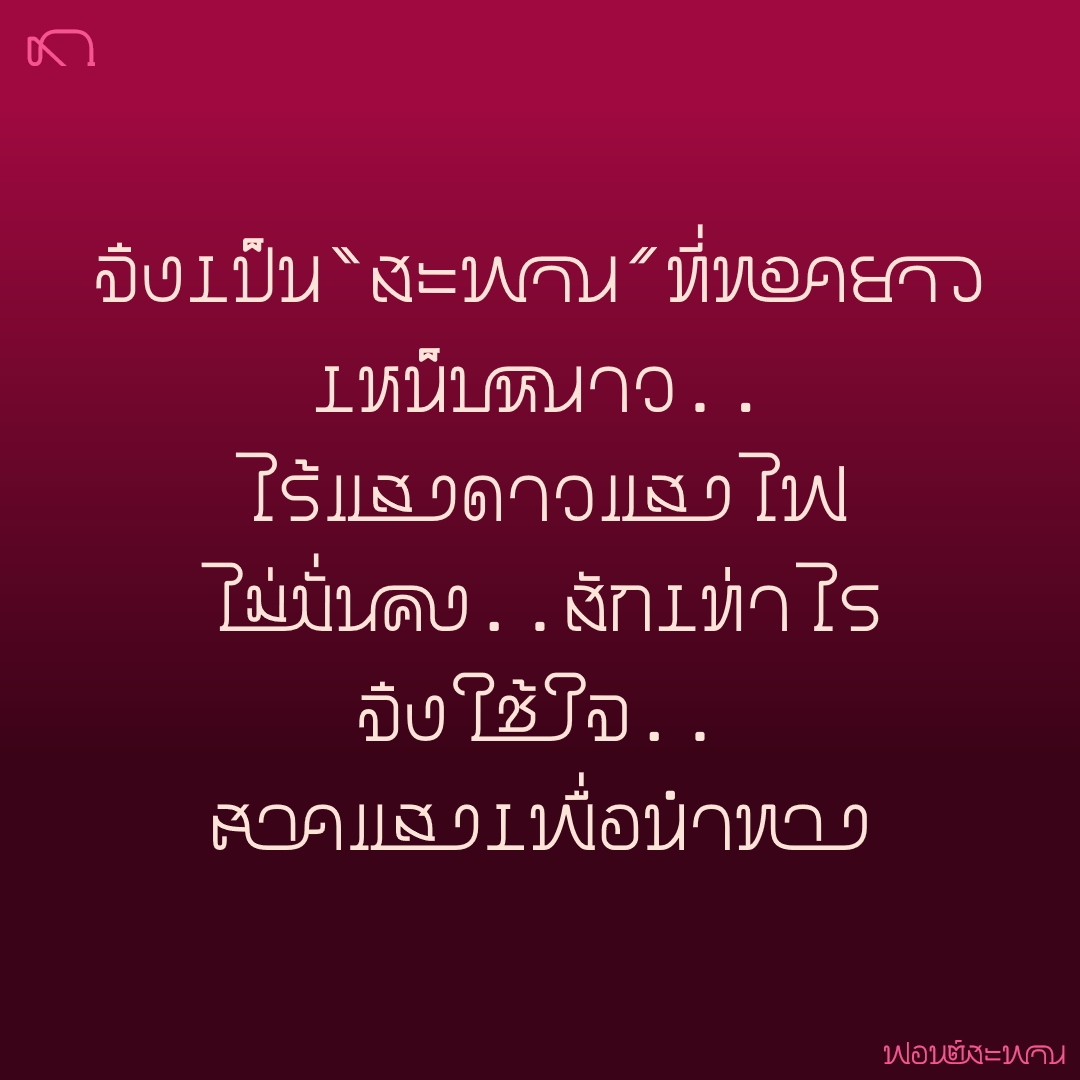
ฟอนต์ สะพาน
ฟอนต์สะพาน แนวอักษรสัมพันธ์ คราวนี้ข้ามคลอง ลอดอุโมงค์ ไปเจอกันจนได้ (ถ้าอยากกีดกันสานสัมพันธ์ ให้กด ฯฯ แทรกกลางเช่นเคย)
ชื่อฟอนต์ : สะพาน
ฟอนต์สะพาน แนวอักษรสัมพันธ์ คราวนี้ข้ามคลอง ลอดอุโมงค์ ไปเจอกันจนได้ (ถ้าอยากกีดกันสานสัมพันธ์ ให้กด ฯฯ แทรกกลางเช่นเคย)